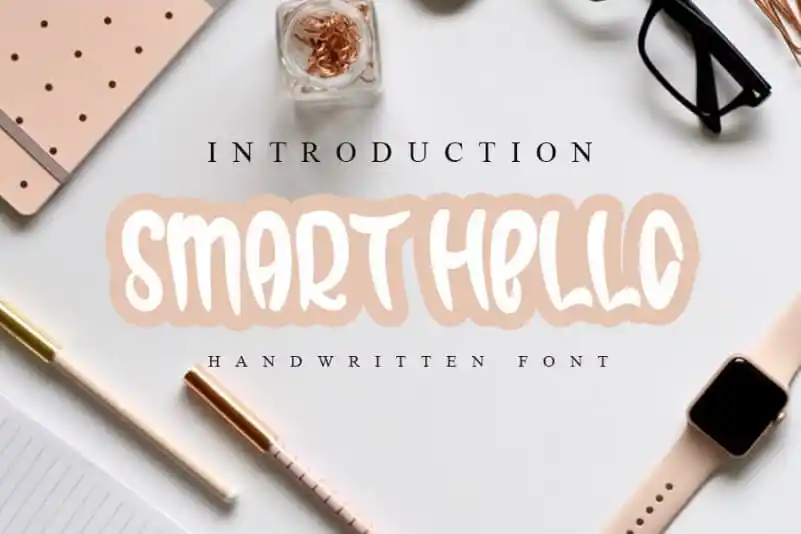
Smart Hello Brush Font – Download Grátis
A Smart Hello Brush Font é uma criação inovadora que resulta de uma incrível fusão entre um canetinha e um lápis, dando ao resultado um ar encantador e autêntico. O designer inermediaSTUDIO conseguiu capturar a essência da escrita à mão tradicional, transformando-a em uma fonte única e bela perfeita para qualquer projeto DIY. Seja ele decorativo ou funcional, esta fonte vai fazer do seu trabalho algo que você pode orgulhar-se de ter feito. Através da Smart Hello Brush Font, deixe o seu trabalho ter vida ao adicionar um toque de personalidade e originalidade à sua obra.